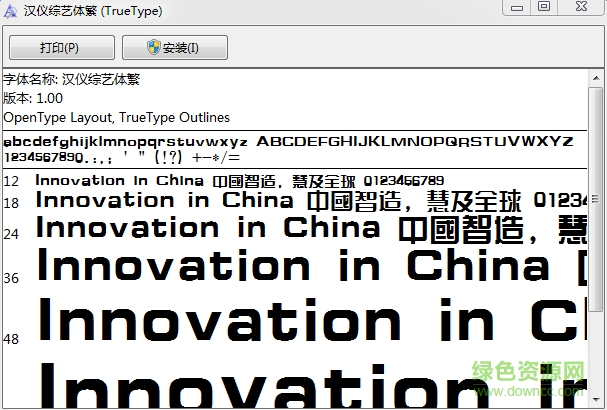
軟件介紹 軟件標(biāo)簽: 漢儀字體 字體 漢儀綜藝體繁體字體是一款很有特色的電腦字體,這款字體寫出來的字很粗厚、均勻,就會給人一種很穩(wěn)重的感覺,小編為大家準(zhǔn)備了這款字體的下載地址,有需要的朋友可以來綠色資源網(wǎng)下載。安裝說明:1.在綠色資源網(wǎng)下載字體包,并解壓縮2.最簡單的安裝方法:雙擊字體文件,點擊安裝按鈕即可2.批量安裝方法:將字體文件放到C:\Windows\Fonts溫馨提示:本站所有字體資源僅供個人學(xué)習(xí)與參考,如需商業(yè)使用請到相關(guān)官網(wǎng)授權(quán) 本字體如果商用,請聯(lián)系漢儀字體官方獲得授權(quán)。 軟件截圖 上一張下一張(1 / 1) 安裝詳細截圖 猜你喜歡 綜藝體 綜藝體 綜藝體是一種結(jié)合了宋體和黑體的特點設(shè)計的藝術(shù)字體,線條張揚,邊角圓潤,筆畫粗黑,效果醒目,辨別度極高,適用的范圍也極其廣泛! 查看更多>> 創(chuàng)藝繁綜藝字體 1.31M/中文/0.0/免費版下載 adzyjt--gb1-0字體 900KB/中文/4.4/下載 咸魚綜藝體 869KB/中文/1.6/下載 安托綜藝體 669KB/中文/3.3/下載 緇忓吀緇艱壓浣撶畝字體 1.23M/中文/6.6/下載 愛度綜藝體 869KB/中文/10.0/簡體ttf下載 其他版本下載 標(biāo)題 大小 更新日期 下載 下載地址 電腦版 漢儀綜藝體繁 點擊報錯 軟件無法下載或下載后無法使用,請點擊報錯,謝謝! 關(guān)閉報錯反饋 請描述您所遇到的錯誤,我們將盡快予以修正,謝謝! *必填項,請輸入內(nèi)容 本類最新 漢儀孟瑞體ttf v1.0 官方版 漢儀字庫免費 132款 阿里巴巴普惠字體 官方ttf版 漢儀字體打包大全 for Mac 蘋果電腦版_ 共131款字體 漢儀純愛情書拼音體 ttf版 漢儀北魏寫經(jīng)w字體 免費版 相關(guān)文章 Photoshop字體安裝使用方法和技巧 如何解決“無法新增字體”問題 Win 7系統(tǒng)安裝字體方法 網(wǎng)頁字體大小設(shè)置方法 怎么改網(wǎng)頁字體大小 在Linux系統(tǒng)中安裝字體的幾種方法 windows7字體顯示問題:打開某些程序的時候顯示的是亂碼 用戶評論 熱門評論 最新評論 發(fā)表評論 查看所有評論(0) 昵稱: 請不要評論無意義或臟話,我們所有評論會有人工審核. 字?jǐn)?shù): 0/500 (您的評論需要經(jīng)過審核才能顯示)